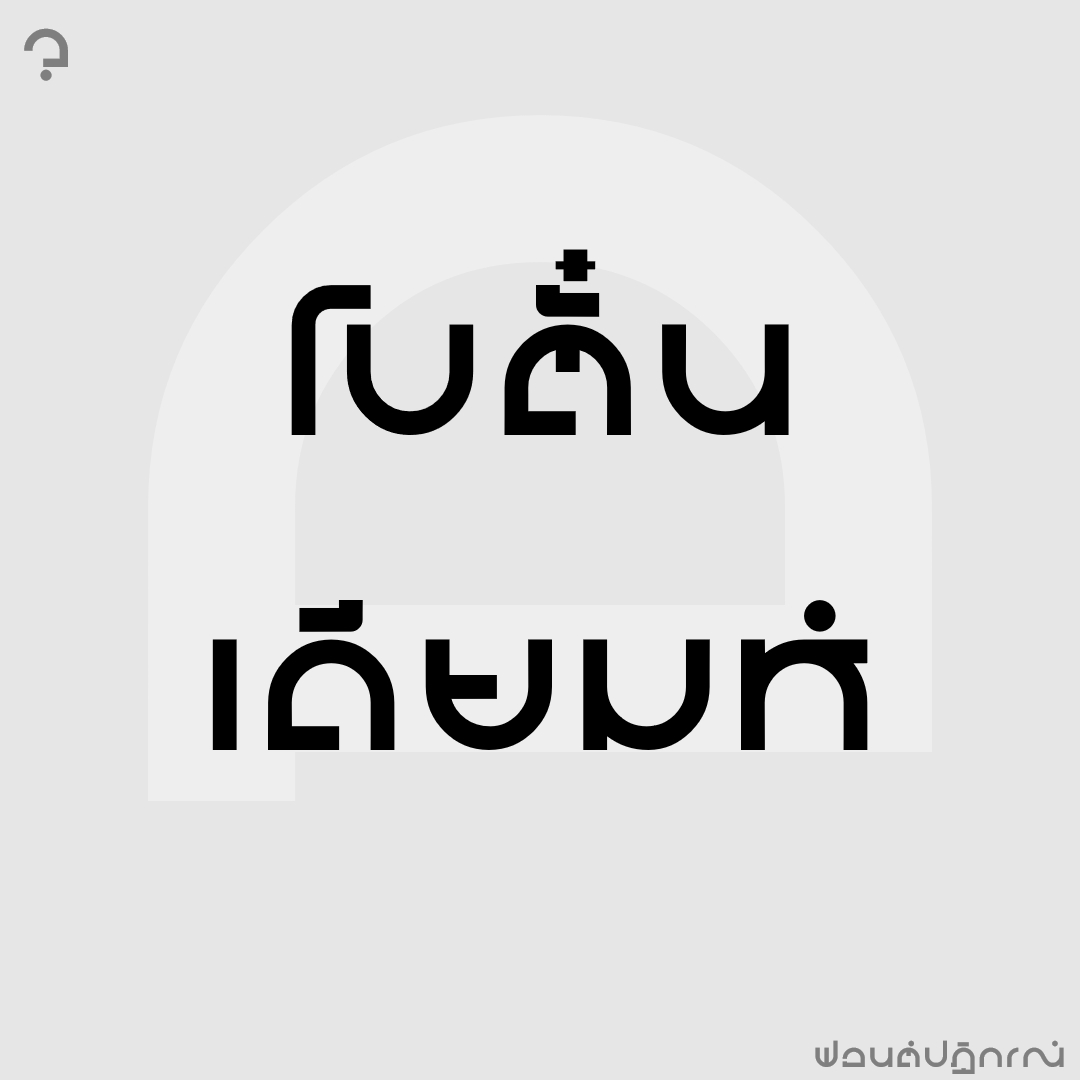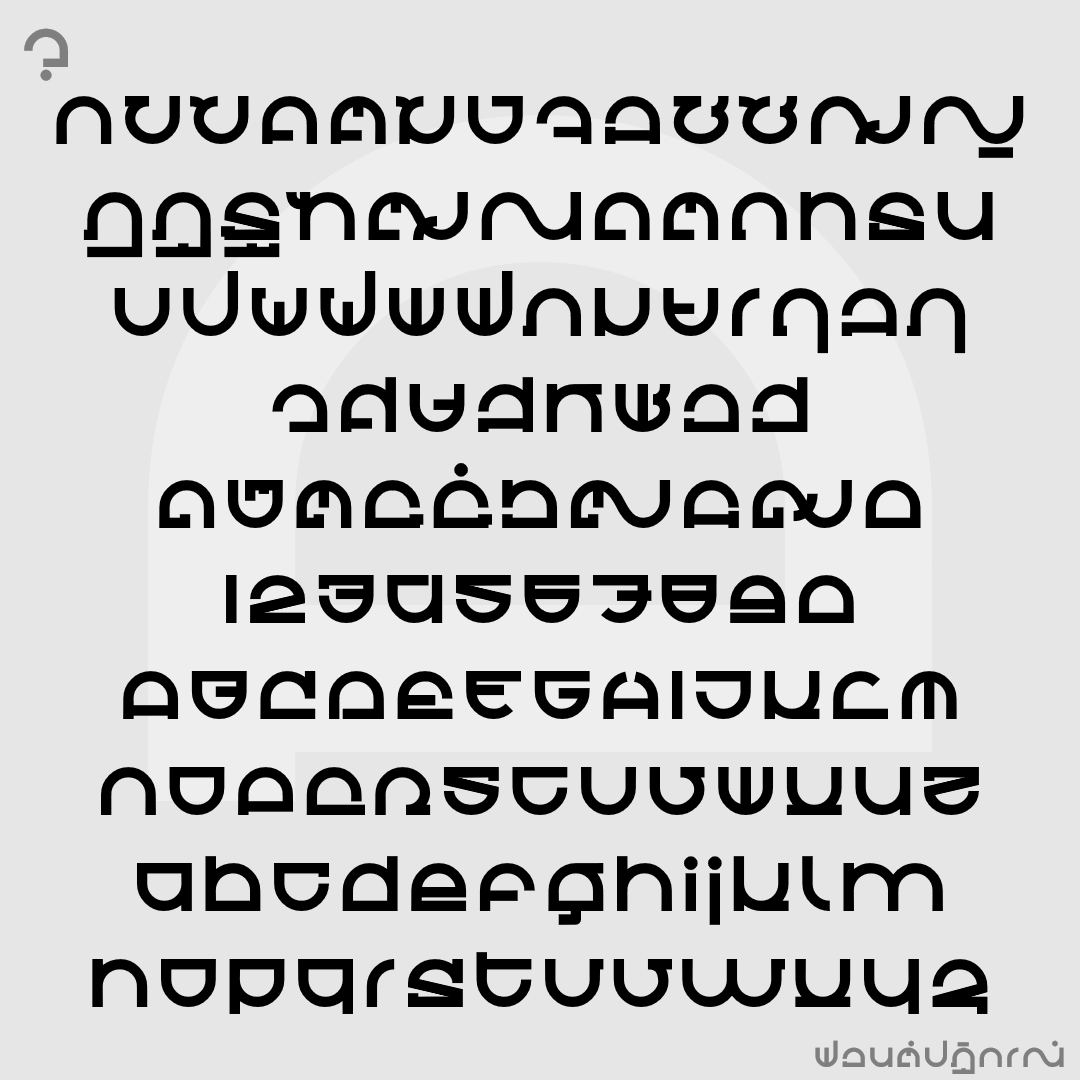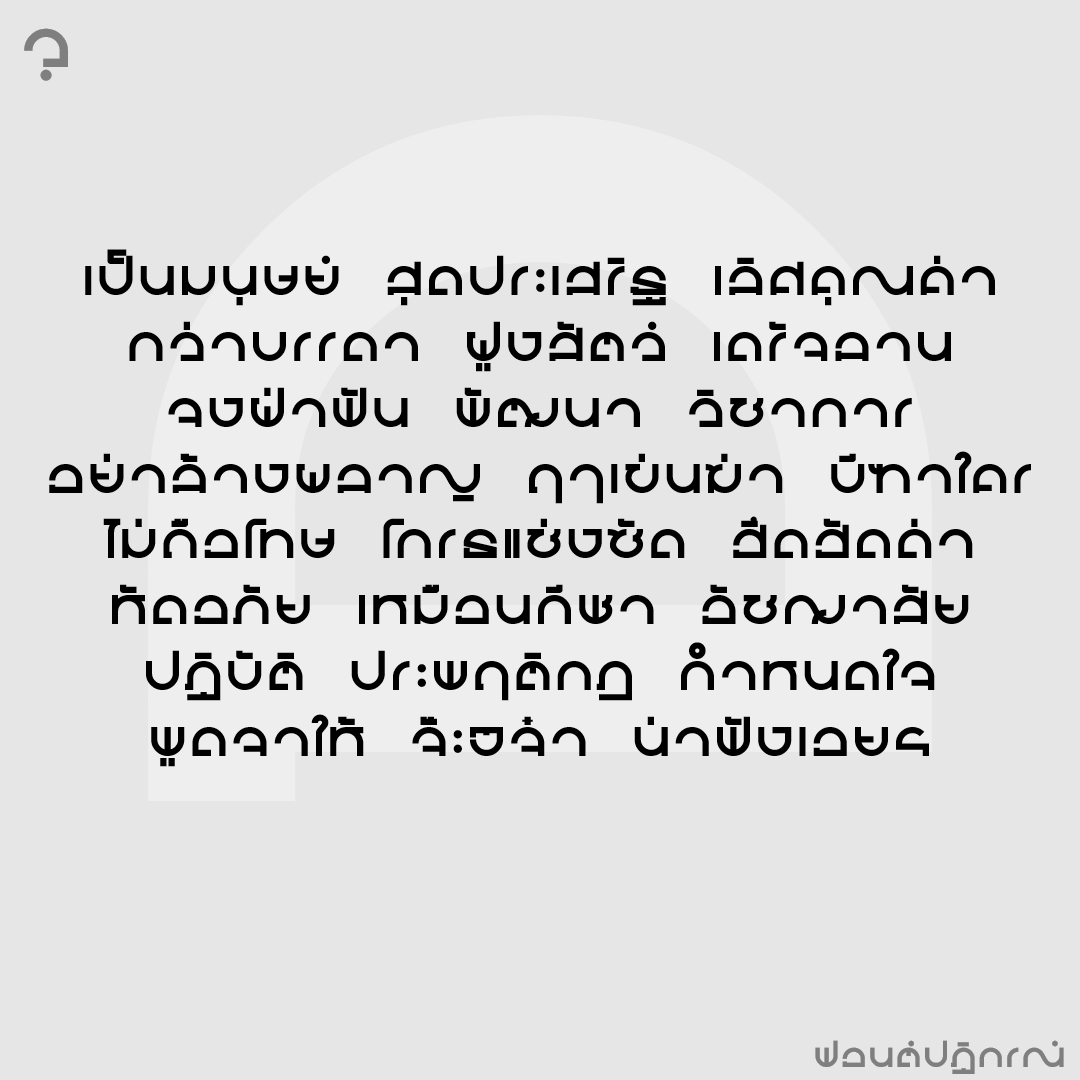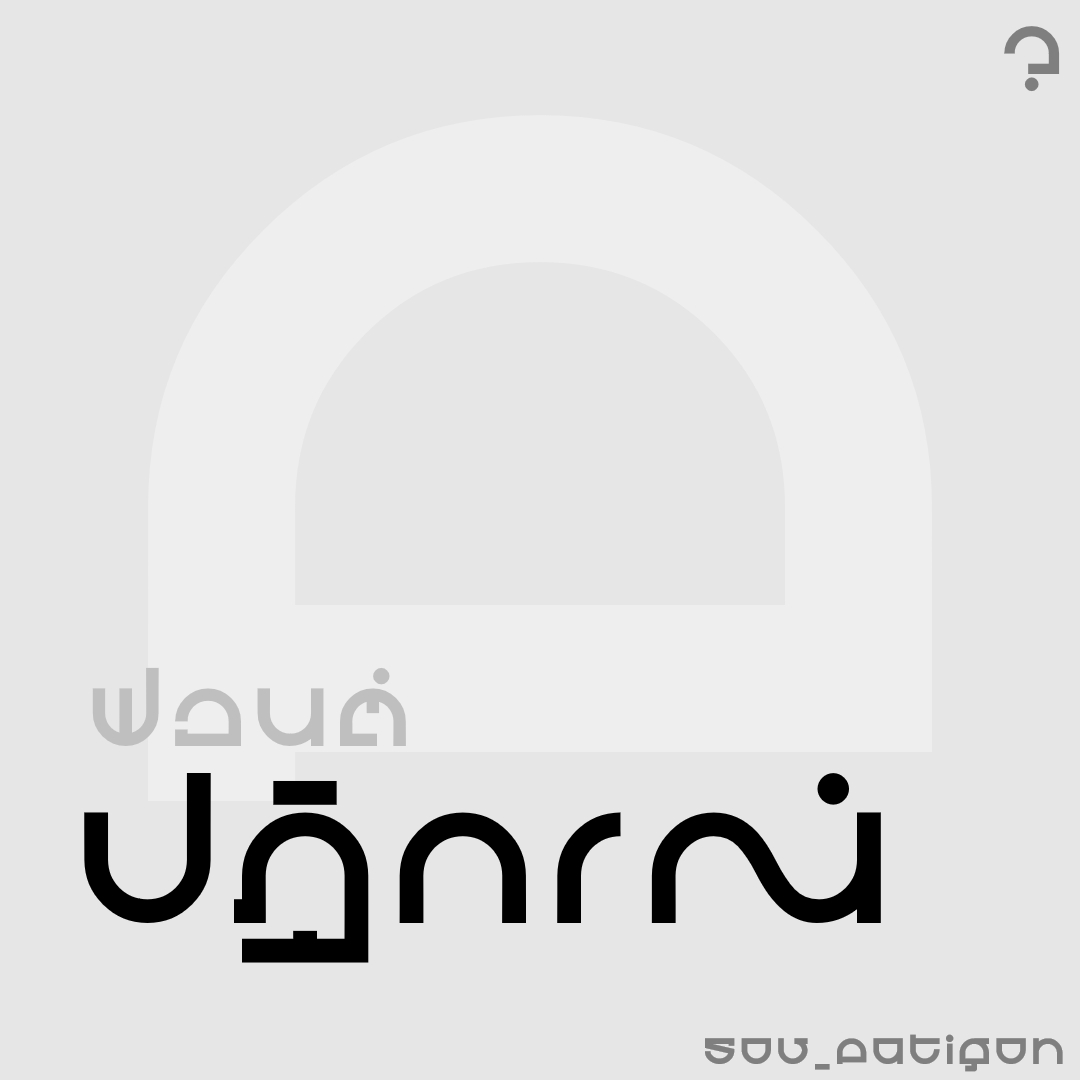
ฟอนต์ ปฏิกรณ์
ต้นทางจาก "ศรีปฏิกรฟิล์ม" แต่ต้องปรับนิดหน่อยเนื่องจากมาทำเป็นฟอนต์ เรื่องความสับสนของอักษร ความเท่แบบต้นฉบับเลยลดลงไปบ้าง
ชื่อฟอนต์ : ปฏิกรณ์
ต้นทางจาก "ศรีปฏิกรฟิล์ม" แต่ต้องปรับนิดหน่อยเนื่องจากมาทำเป็นฟอนต์ เรื่องความสับสนของอักษร ความเท่แบบต้นฉบับเลยลดลงไปบ้าง